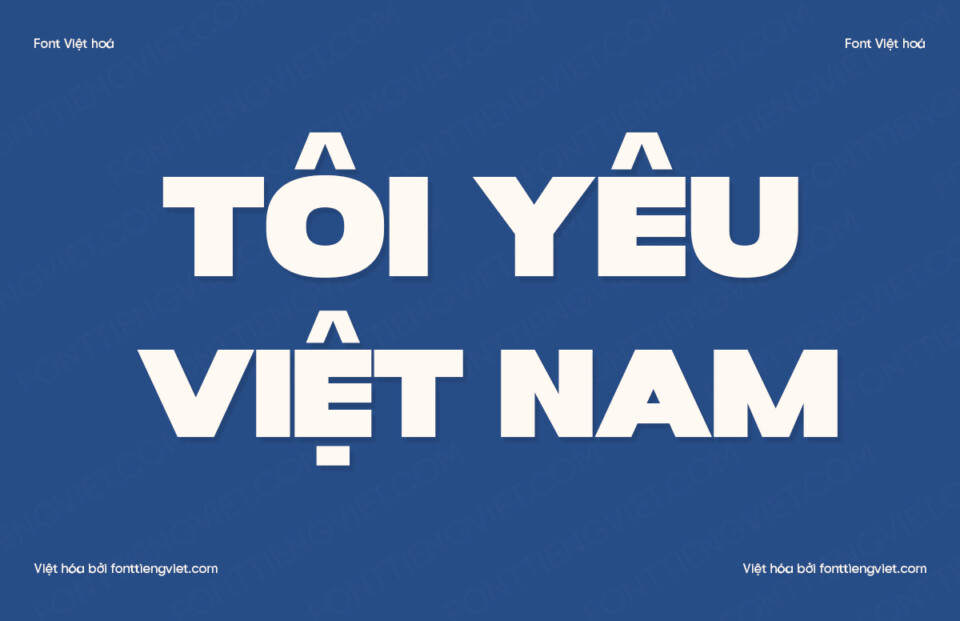
Font Việt hóa 1FTV VIP DINKO
Tải Ngay Font Việt hóa 1FTV VIP DINKO – Font Chữ Sáng Tạo Cho Thiết Kế Giáo Dục
Giới thiệu về bộ Font Việt hóa 1FTV VIP DINKO
Trong thế giới thiết kế đồ họa hiện đại, việc lựa chọn một bộ font chữ vừa đảm bảo tính thẩm mỹ, vừa hỗ trợ đầy đủ tiếng Việt là điều vô cùng quan trọng. Font Việt hóa 1FTV VIP DINKO nổi lên như một giải pháp hoàn hảo cho các nhà thiết kế đang tìm kiếm sự phá cách nhưng vẫn giữ được nét gần gũi. Đây là một bộ Font Miễn Phí được tinh chỉnh kỹ lưỡng về dấu câu, giúp người dùng tại Việt Nam dễ dàng ứng dụng vào nhiều dự án khác nhau từ học tập đến công việc chuyên môn. 1FTV VIP DINKO không chỉ là một phông chữ thông thường, mà còn là công cụ truyền tải cảm xúc mạnh mẽ qua từng nét vẽ tinh tế và hiện đại.
Đặc điểm nổi bật của Font Việt hóa 1FTV VIP DINKO
Thiết kế độc đáo và hiện đại
Sự khác biệt lớn nhất của Font Việt hóa 1FTV VIP DINKO nằm ở cấu trúc chữ cái được cách điệu một cách thông minh. Các đường nét được bo tròn nhẹ nhàng, tạo cảm giác thân thiện và dễ nhìn. Điều này giúp bộ font trở nên cực kỳ phù hợp cho các em học sinh khi làm bài thuyết trình hoặc cho các giáo viên khi soạn thảo giáo án điện tử sinh động. Mỗi ký tự trong bộ font đều được trau chuốt để đảm bảo sự cân đối về thị giác, giúp văn bản trở nên chuyên nghiệp hơn bao giờ hết.
Khả năng tương thích và tối ưu hóa
Bộ font này được tối ưu hóa để hiển thị tốt trên cả màn hình kỹ thuật số và các bản in ấn thực tế. Dù bạn sử dụng các phần mềm chuyên nghiệp như Photoshop, Illustrator hay các ứng dụng văn phòng cơ bản như Word và PowerPoint, 1FTV VIP DINKO vẫn hoạt động mượt mà mà không gặp lỗi hiển thị dấu tiếng Việt – một vấn đề thường gặp ở các bộ font ngoại quốc chưa được việt hóa chuẩn. Chính sự ổn định này đã giúp nó trở thành lựa chọn ưu tiên hàng đầu trong cộng đồng thiết kế Việt.
Ứng dụng thực tế của Font Việt hóa 1FTV VIP DINKO
Sáng tạo nội dung giáo dục
Với phong cách trẻ trung, Font Việt hóa 1FTV VIP DINKO thường xuyên xuất hiện trong các poster trường học, bìa sách giáo khoa hoặc các ấn phẩm truyền thông của các câu lạc bộ sinh viên. Nó giúp nội dung truyền tải trở nên thú vị hơn, bớt đi sự khô khan của các văn bản truyền thống. Ngoài ra, các bạn học sinh có thể dùng font chữ này để trang trí tập vở hoặc thiết kế thiệp chúc mừng thầy cô, bạn bè một cách đầy sáng tạo.
Thiết kế thương hiệu và truyền thông
Không chỉ giới hạn trong giáo dục, bộ font còn được ứng dụng rộng rãi trong thiết kế logo, bao bì sản phẩm và hình ảnh quảng cáo trên mạng xã hội. Sự linh hoạt trong kiểu dáng giúp nó dễ dàng kết hợp với nhiều phong cách thiết kế từ tối giản đến phức tạp, mang lại hiệu quả thị giác cao cho người xem ngay từ cái nhìn đầu tiên.
Kết luận về bộ Font Việt hóa 1FTV VIP DINKO